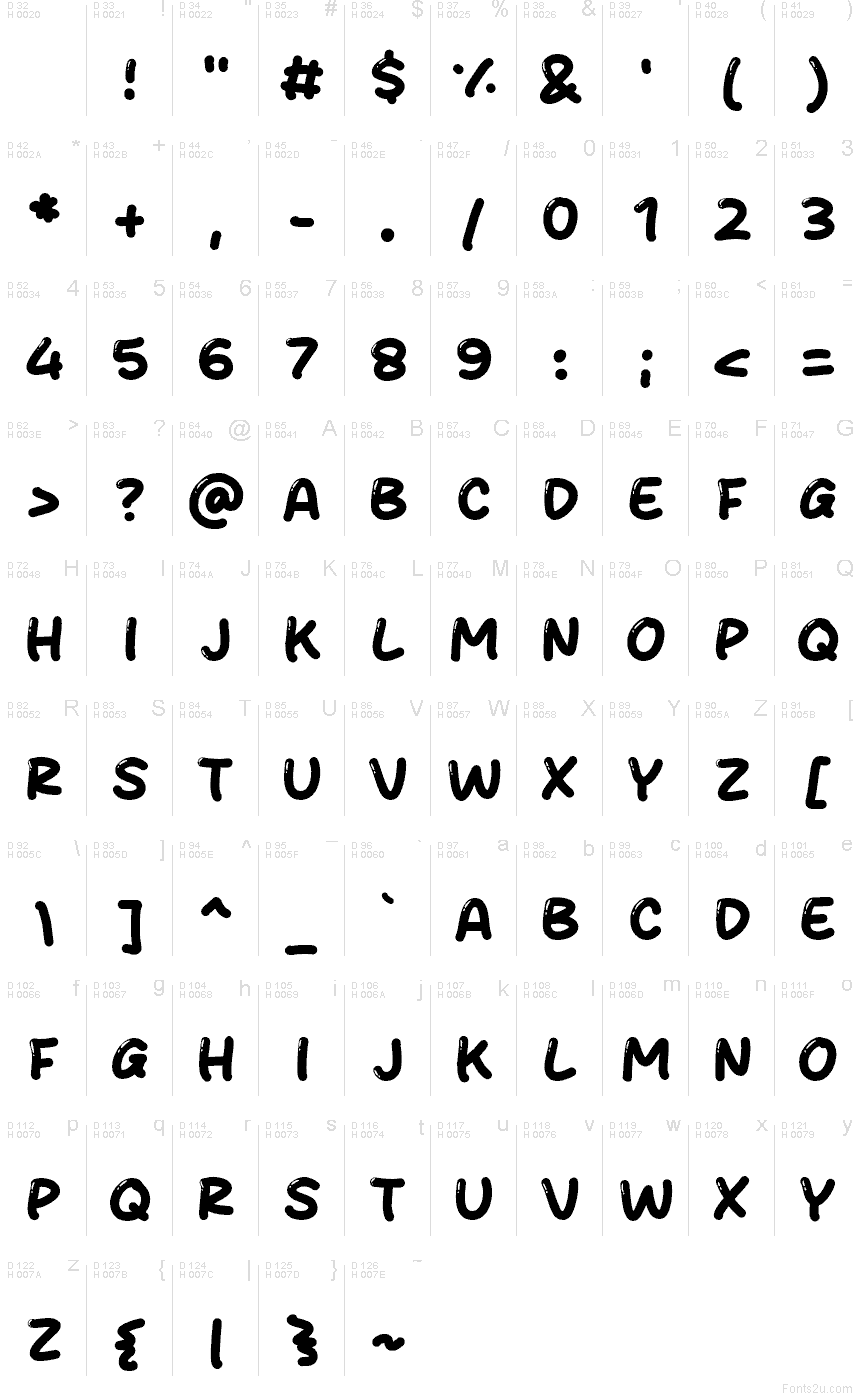
Candy Fruits od Origin Type je bezplatné kreslené titulkové písmo s bacuľatými, mierne nepravidelnými veľkými písmenami a živým, ručne kresleným dojmom. Drobné odlesky vnútri znakov pripomínajú lesklé cukríky, zatiaľ čo zaoblené rohy a jemne vlnité tvary dodávajú dizajnu hravý, nie strnulý charakter.
Toto bezplatné písmo sa skvele hodí na obaly cukroviniek, obálky detských kníh, pozvánky na večierky, samolepky a hravú brandovú grafiku. Dobre funguje aj v krátkych nadpisoch a na titulných kartách, kde majú nadrozmerné tvary a cukríkové detaily dostatok priestoru, aby vynikli svojou jednoduchou vizuálnou nadsázkou.